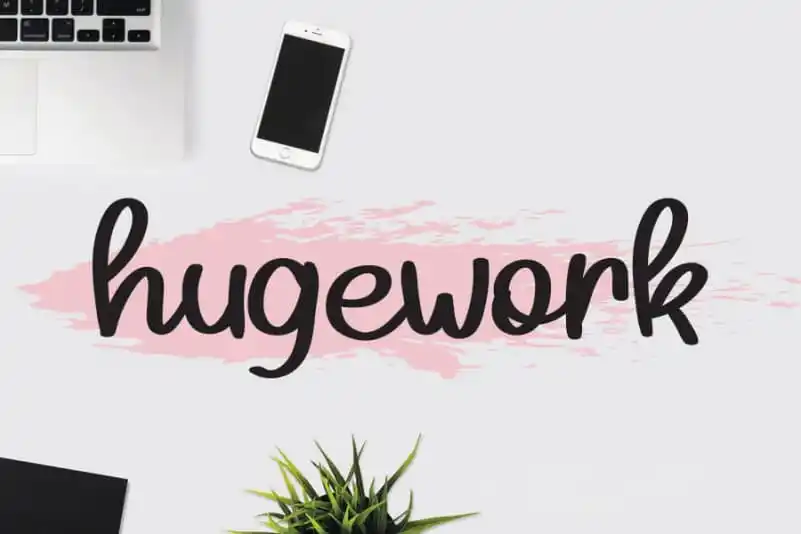
Hugework Handwritten Font – Fonte Grátis
Hugework Handwritten Font
A Hugework Handwritten Font é uma fonte escrita à mão com um toque suave e amigável. Suas formas únicas e naturais a tornam perfeita para uma variedade de designs, limitada apenas pela imaginação do designer ou criador. Essa fonte traz consigo uma sensação de serenidade, ideal para aplicar em projetos que buscam transmitir calma e simplicidade. A Hugework é perfeitamente adaptável a múltiplos estilos gráficos, desde cartões de aniversário até designs de loja customizados. Seu estilo natural faz com que qualquer projeto assuma um ar pessoal e confortável, tornando-a uma opção popular para aqueles que desejam dar vida às suas criações de maneira autêntica e emocionalmente contagiante. Esta fonte não apenas adicionará um toque de personalização a seus projetos, como também ajudará em criar uma conexão mais profunda com seu público. Com Hugework Handwritten Font, você terá ao seu dispor um aliado ideal para expressar sua identidade visual de maneira única e única.